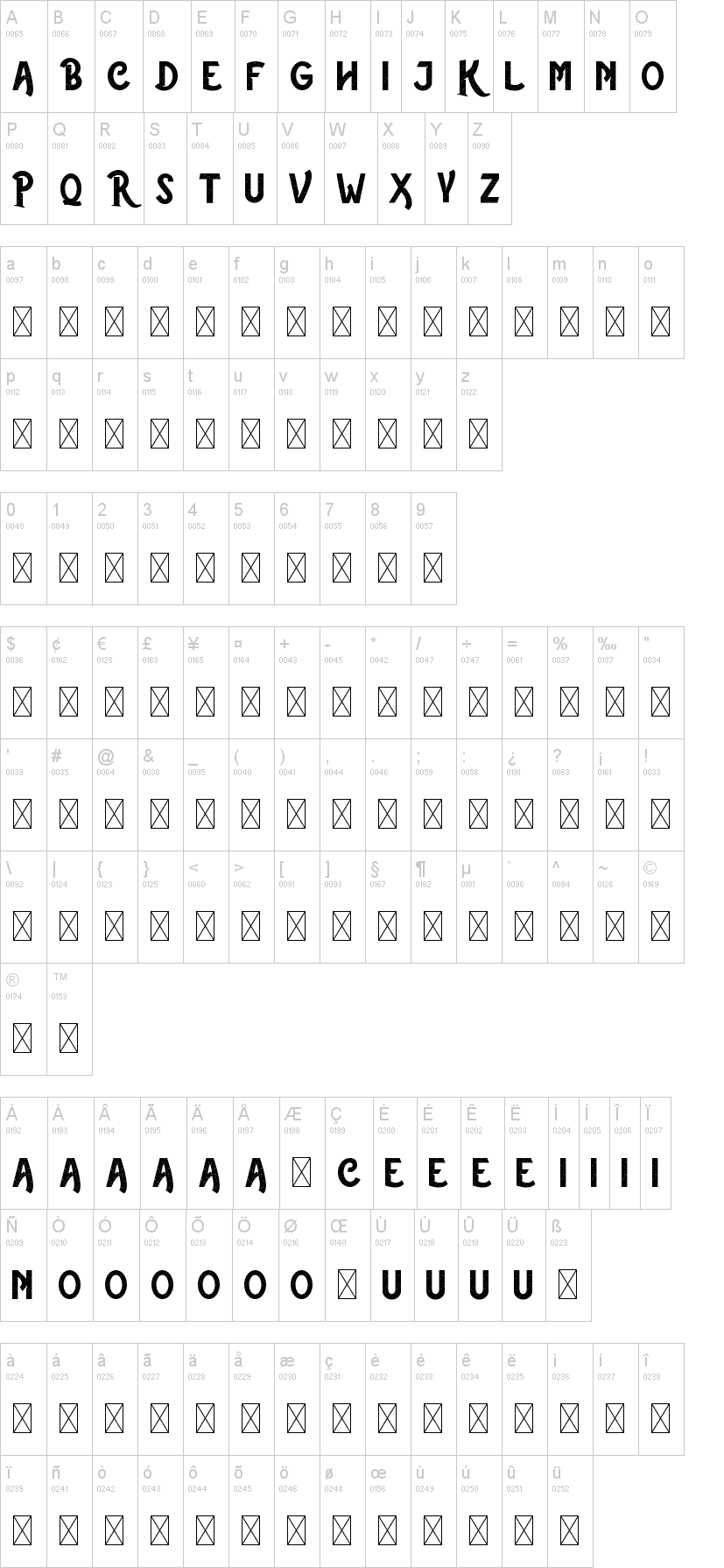
The Rustic
The Rustic 字体是一款风格独特的手写字体,由图形设计师 Hustle Supply Co. 设计。该字体在设计上强调了粗糙、自然和干净的感觉,同时保持了足够的可读性和可用性。每个字母都采用了不同的手写笔画,使得该字体看起来非常有趣和生动。 The Rustic 字体包括大小写字母、数字、标点符号和特殊字符,可以在各种设计项目中使用。该字体适合于各种场合,比如海报、标志、包装、书籍封面、手册和网站设计等。 总的来说,The Rustic 字体是一种非常具有创意性和魅力的手写字体,可以为你的项目增添独特的风格和个性。
The Rustic是一款非常不错的手写艺术字体,具有很好的视觉感,适合于文化类的宣传设计、商业类品牌的广告和产品包装设计以及个性化文字排版等较多场景。